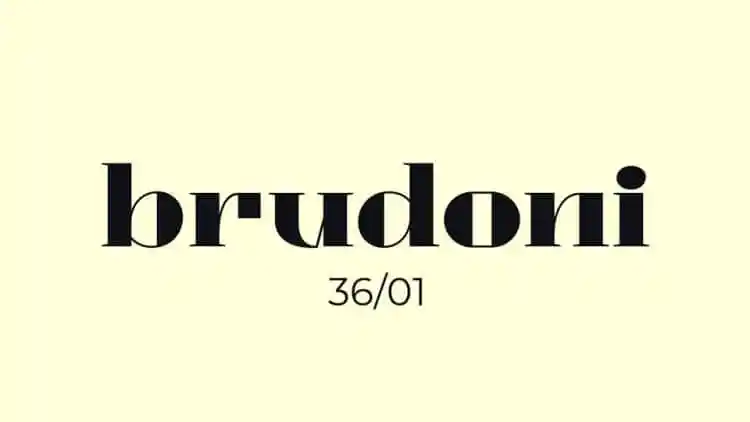
Brudoni Serif Font – Download Grátis
Introduzimos a Brudoni Serif Font, uma tipografia serif com alto contraste que é elegante e possui características únicas, mantendo-se moderna quando se utiliza em produtos de design. Ideal para aplicativos, logotipos, materiais promocionais, headlines, linhas de roupas e outros tipos de material gráfico, esta fonte oferece uma variedade de opções para personalizar seus projetos visuais. Com seu estilo sóbrio mas não formal, a Brudoni Serif se destaca entre as outras fontes serif existentes, tornando-a uma excelente escolha para designers que procuram um equilíbrio perfeito entre modernidade e sofisticação.